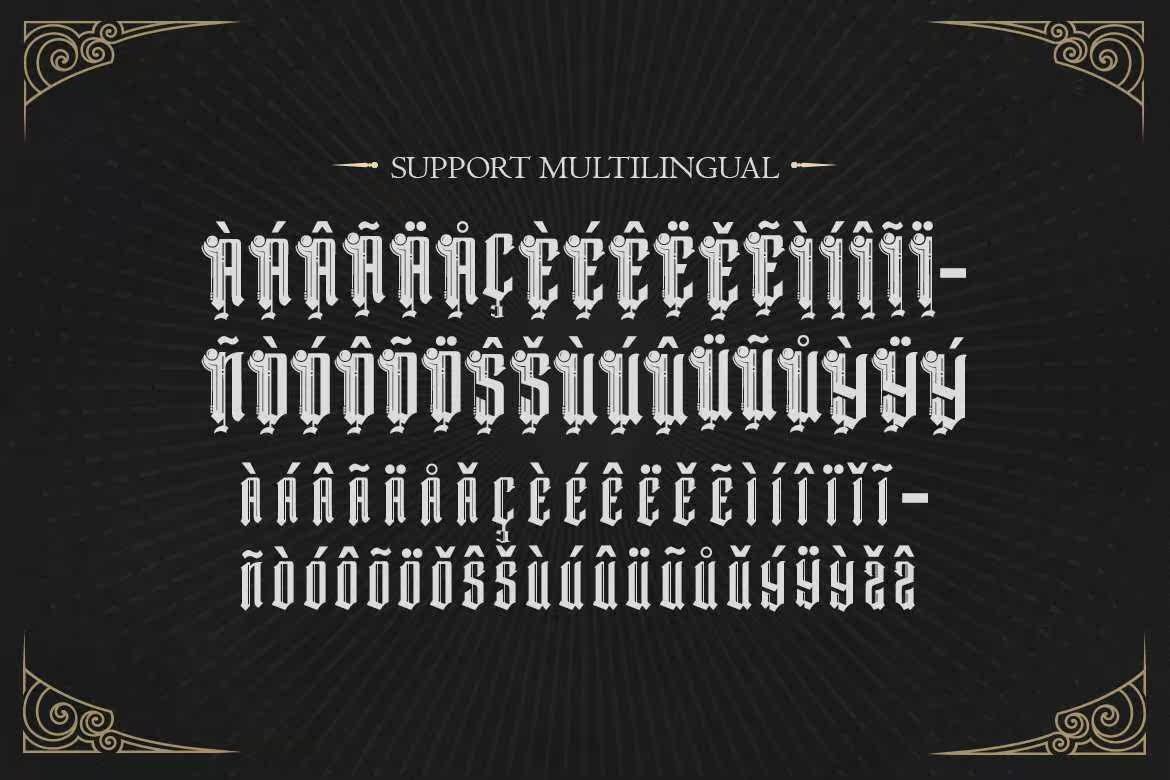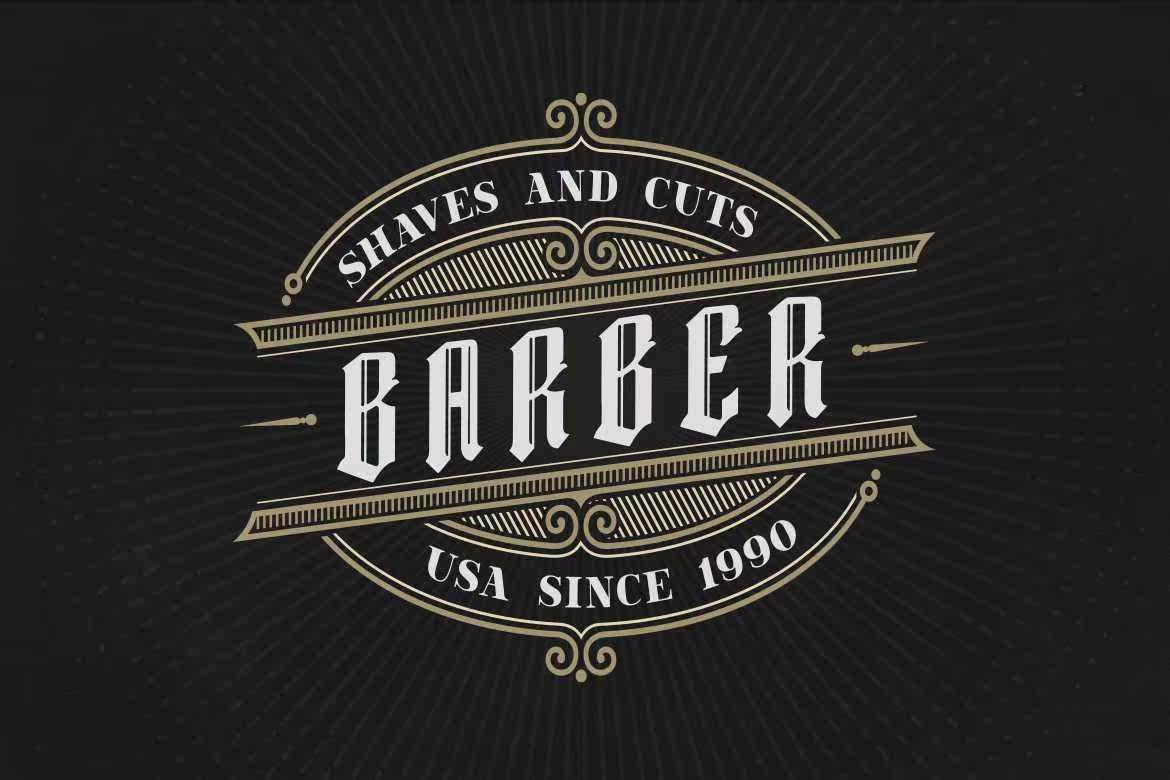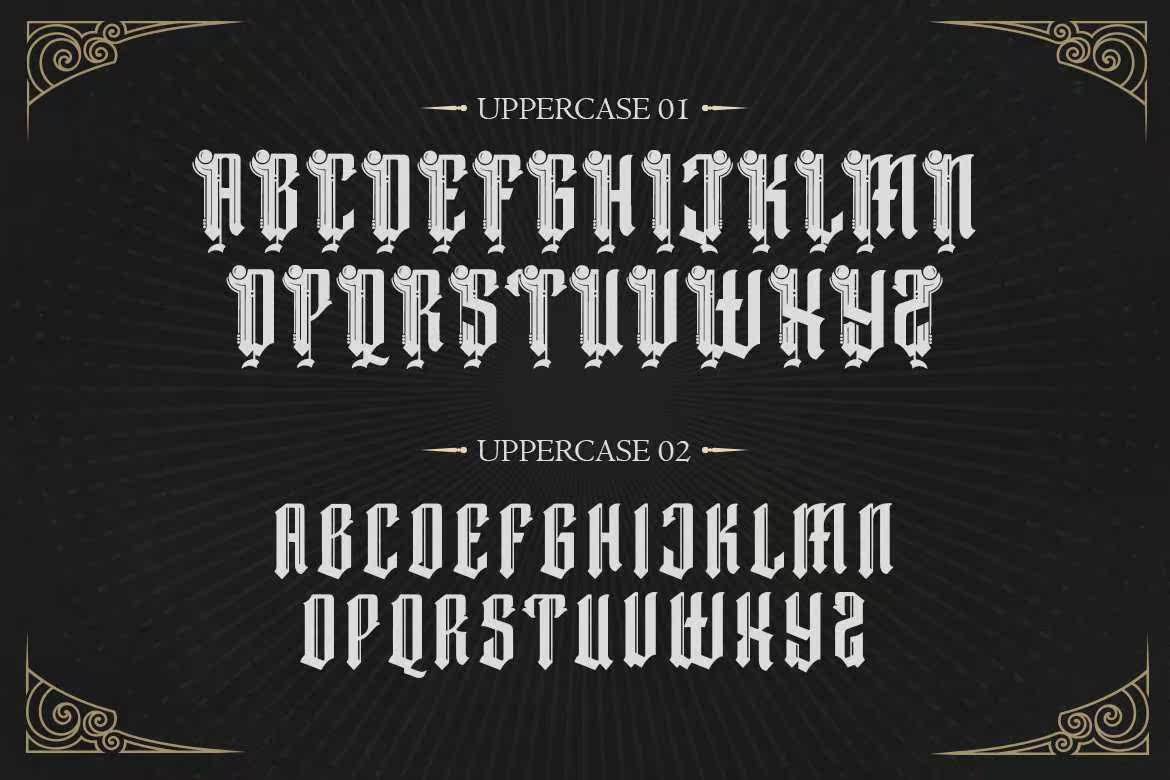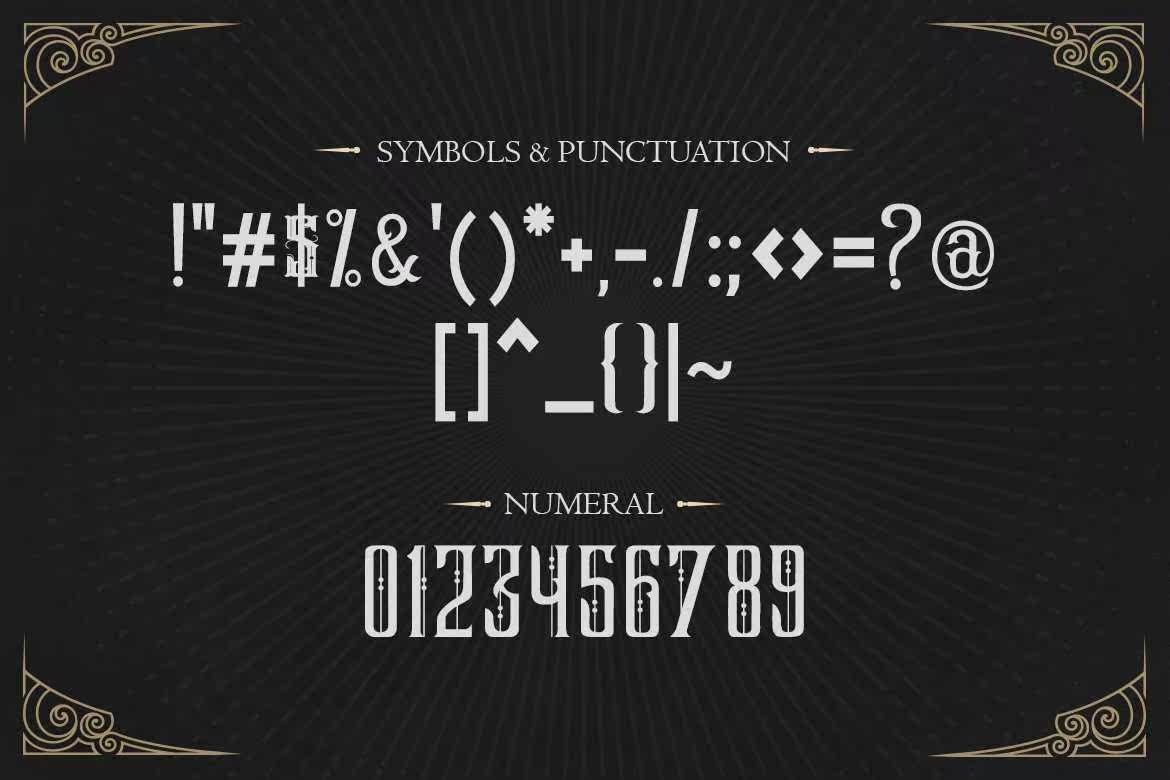
DarkMagicisabold,gothicstyledblackletterfont。它正在定位和增加需要强接触和经典设计的设计。添加到您的项目中,您将不会被点名。完整版本下载此处:DarkMagicisabold,获取StyledBlackleterFont.ItismPosing和IncrediblyadeptForDesign要求StrongTouch和ClassicDesign.AdditConfidentialy到您的项目中,您将不会在此处下载TBedisPointed.FullVersionDownload: